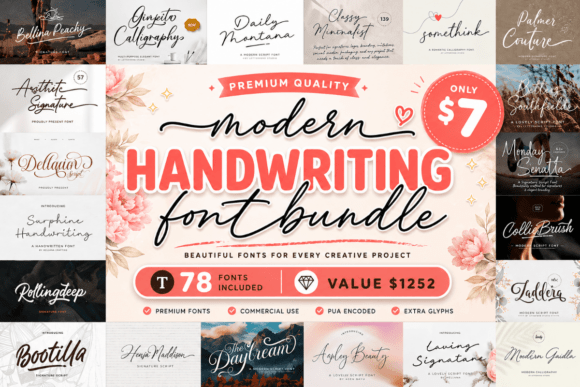
Modern Handwriting Font Bundle
Die richtigen Designelemente zu finden, kann eine Herausforderung sein, aber Modern Handwriting Font Bundle bietet eine außergewöhnliche Sammlung, die Ihre Arbeit sofort aufwertet.
Egal, ob Sie POD-Produkte (Print on Demand), Hochzeitseinladungen oder Social-Media-Grafiken erstellen, Modern Handwriting Font Bundle ist die ideale Wahl.